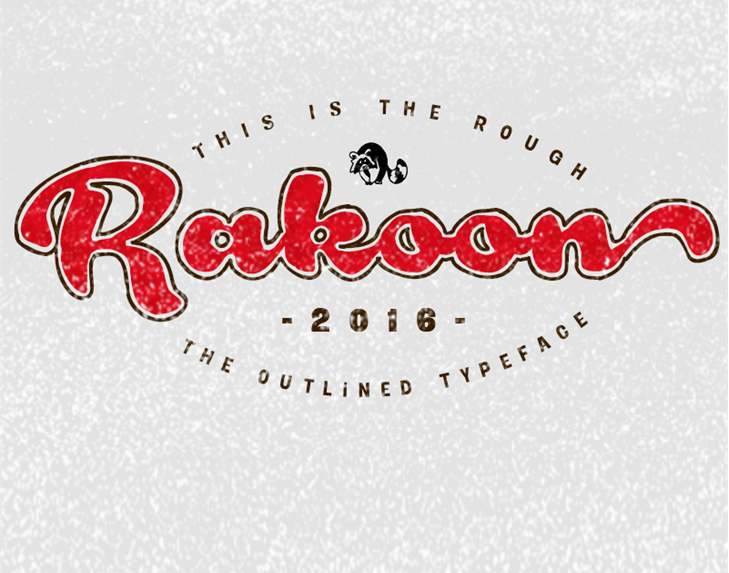
A Rough Rakoon Font é uma escolha perfeita para adicionar um toque irreverente e divertido a qualquer projeto visual. Desenvolvida pelo designer sueco Måns Grebäck, essa fonte brinca com os limites tradicionais da tipografia, oferecendo linhas robustas e curvas irregulares que trazem uma sensação de liberdade inusitada ao seu design. Ideal para aplicativos como logotipos ou materiais publicitários onde você deseja manter um ar descontraído, a Rough Rakoon é perfeita para quem procura uma fonte de categoria Playful Fonts que não se contenta em ser apenas estilosa e profissional. Visite www.mansgreback.com/fonts/rough-rakoon para adquirir sua licença comercial desta fonte única e divertida.